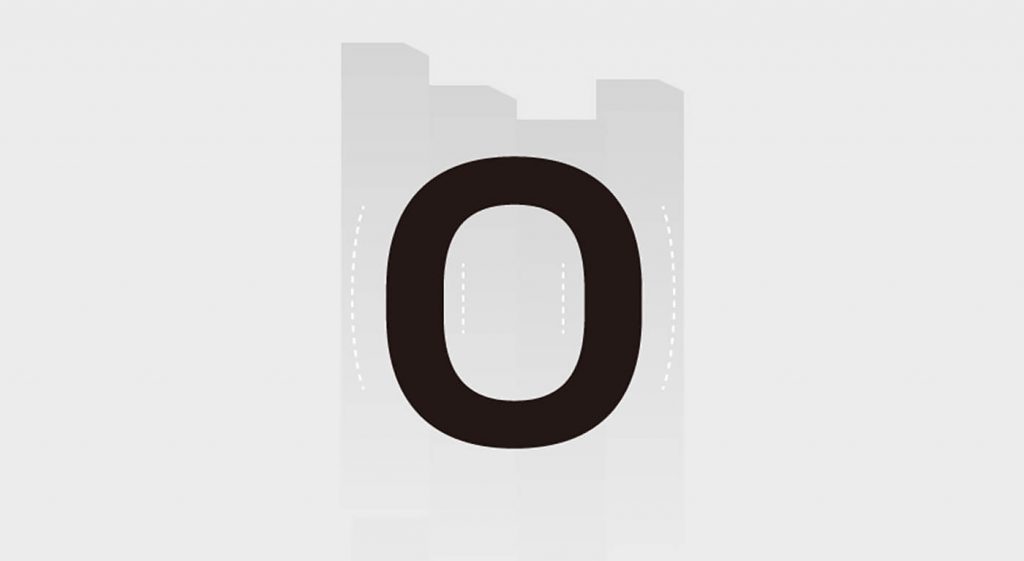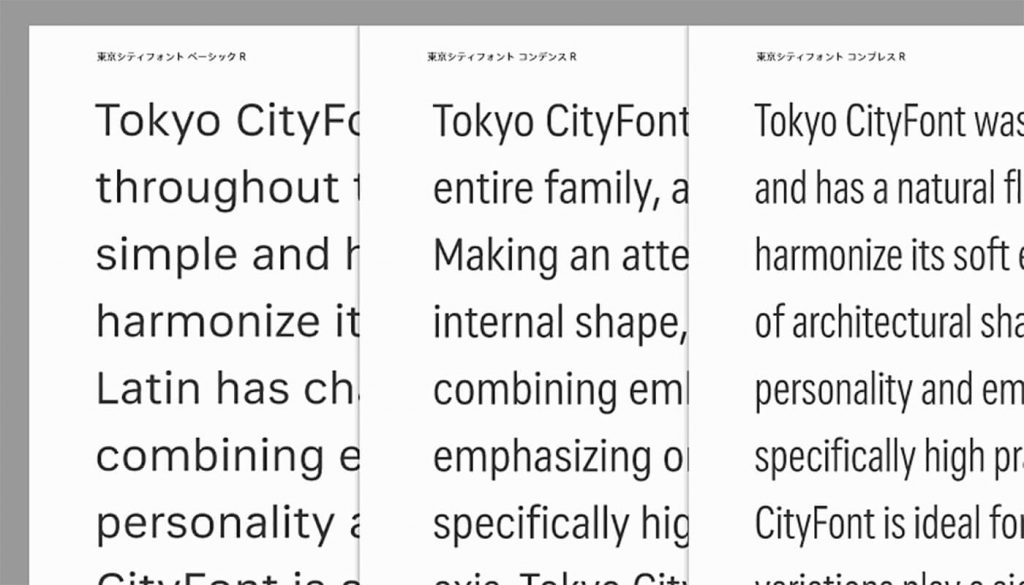
東京シティフォント開発ストーリー01「欧文デザインの特徴」
東京シティフォントは日本デザインセンターによる街区表示用書体として提供したことから始まりました。粋と言うテーマを中心に、程よい抑揚と少し長体で設計されたデザインを一つの答えとしています。その後、製品版にする際に今までの重要なテーマである交通機関などのサインに加えて、東京の建築群との相性を考慮したデザインを新たに制作しています。
全体的にジオメトリックな雰囲気を持ち、外側はやわらかな、内部は直線でがっちりとしたデザインです。また、正体からコンデンスまで、さまざまな範囲で使用できるように用意されています。